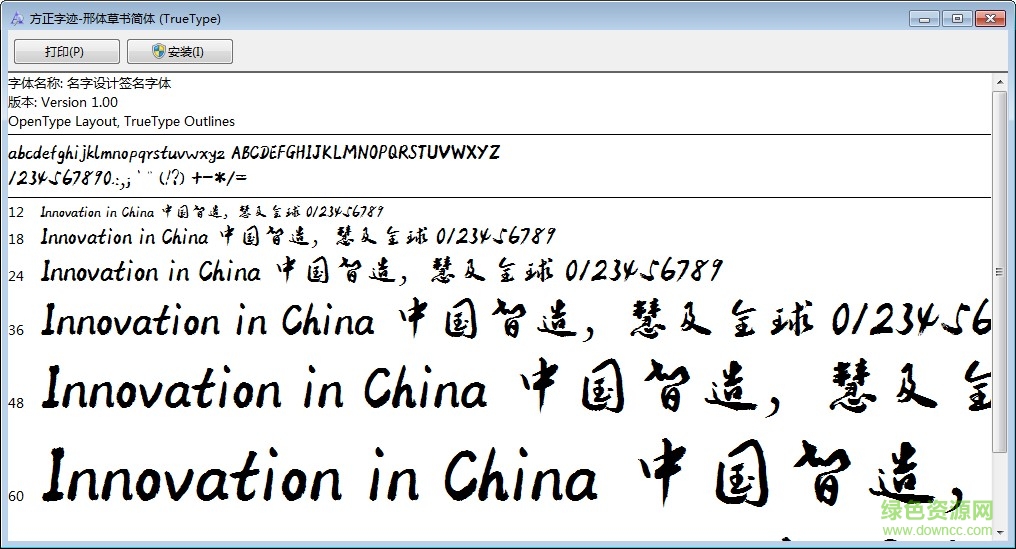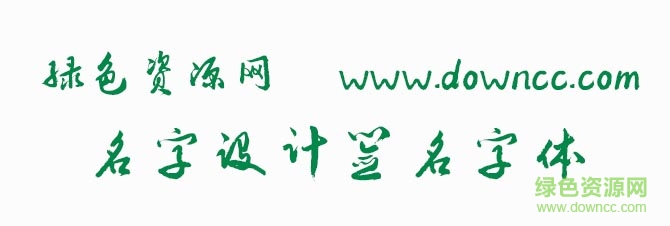
名字設(shè)計(jì)簽名字體
名字設(shè)計(jì)簽名字體是一款專(zhuān)為用戶(hù)打造的名字設(shè)計(jì)字體,有需要的朋友千萬(wàn)不要錯(cuò)過(guò),用戶(hù)自己設(shè)計(jì)簽名、廣告藝術(shù)設(shè)計(jì)、平面設(shè)計(jì)都可以使用。小編為大家提供免費(fèi)下載地址。歡迎大家來(lái)綠色資源網(wǎng)踴躍下載哦!